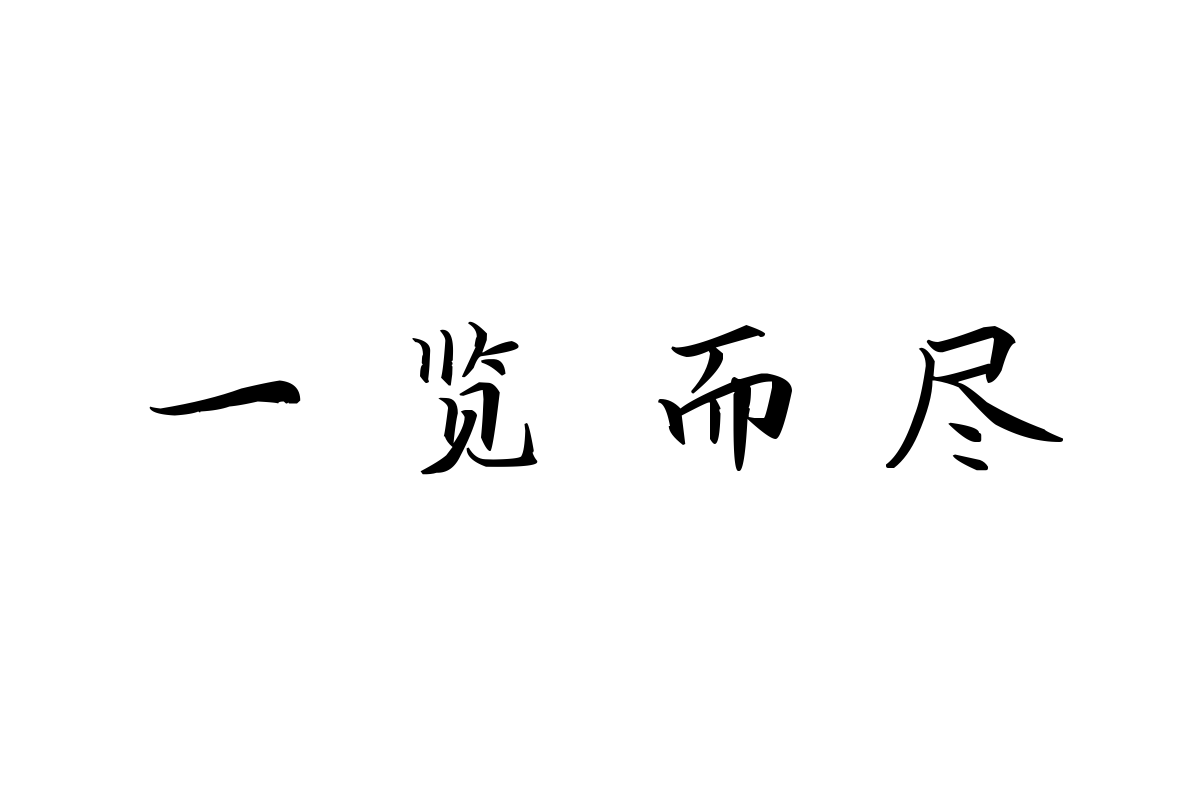
汉呈王天喜抄经体是一种书法字体,它的特点是笔画流畅自然,结构严谨紧凑,给人一种古朴典雅的感觉。这种字体的特点主要体现在以下几个方面:
1. 笔画流畅自然:汉呈王天喜抄经体的笔画线条流畅,没有过多的装饰和修饰,给人一种朴实无华的感觉。
2. 结构严谨紧凑:这种字体的结构紧凑,每个字的笔画都安排得恰到好处,使得整个字体看起来非常和谐统一。
3. 古朴典雅:汉呈王天喜抄经体具有浓厚的古典气息,给人一种古朴典雅的感觉,非常适合用于书写诗词、文章等文学作品。
4. 易于识别:由于这种字体的特点鲜明,所以非常容易被人们所识别,便于人们学习和使用。
总的来说,汉呈王天喜抄经体是一种具有独特韵味的书法字体,它的出现丰富了我们的书法艺术形式,也为我们提供了更多的选择空间。